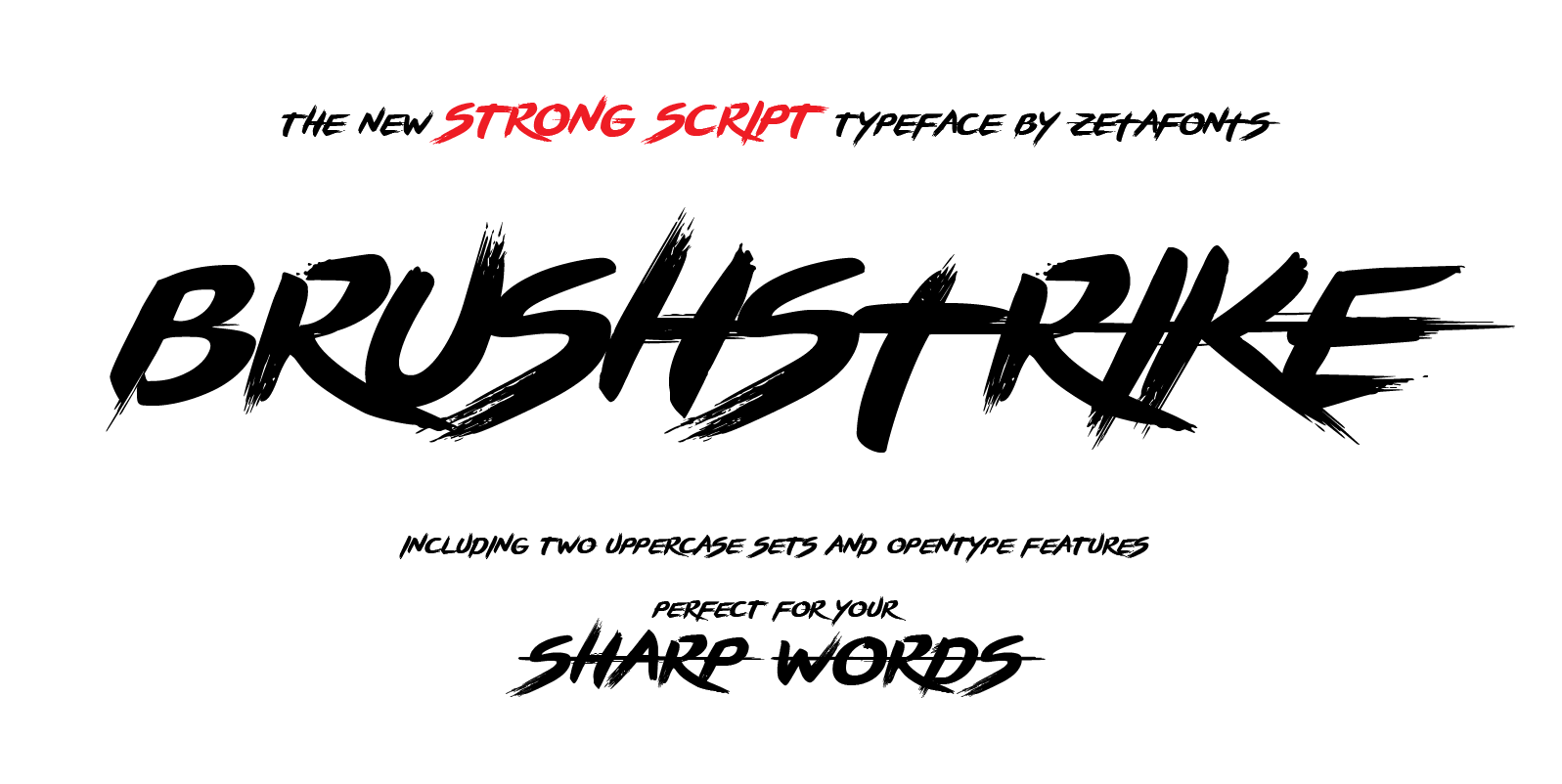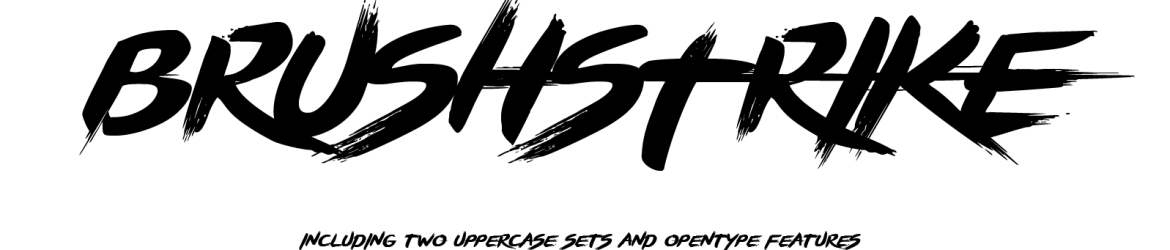
A Brushstrike Font é uma tipografia desenvolvida por Francesco Canwcaro, disponível com um conjunto duplo de letras maiúsculas (tradicionais e quebradas). Esta fonte é perfeita para designers gráficos que buscam uma sensação natural e agradável. Ideal para títulos e destaque em layouts de design, ela traz o deslumbrante charme das escreveres artesanais às suas criações digitais. A Brushstrike oferece um toque único que combina perfeitamente com qualquer projeto gráfico, seja ele digital ou impresso.